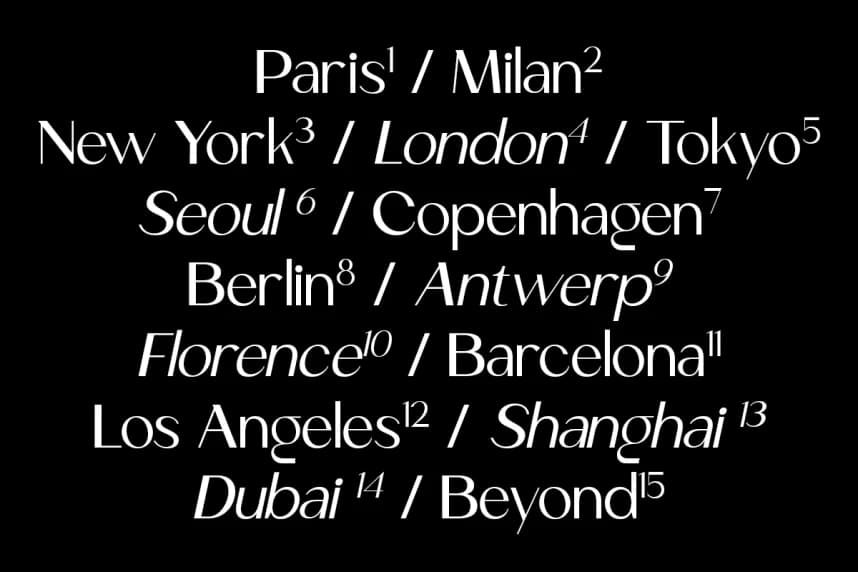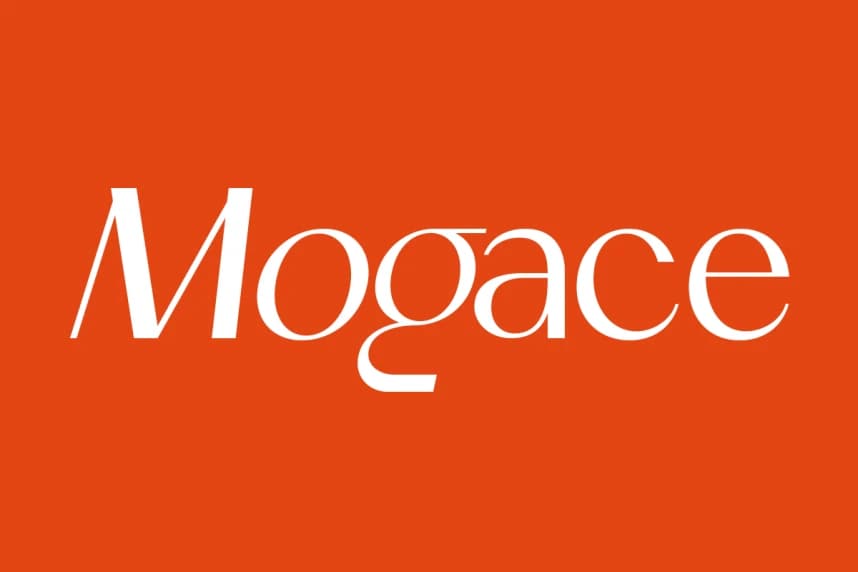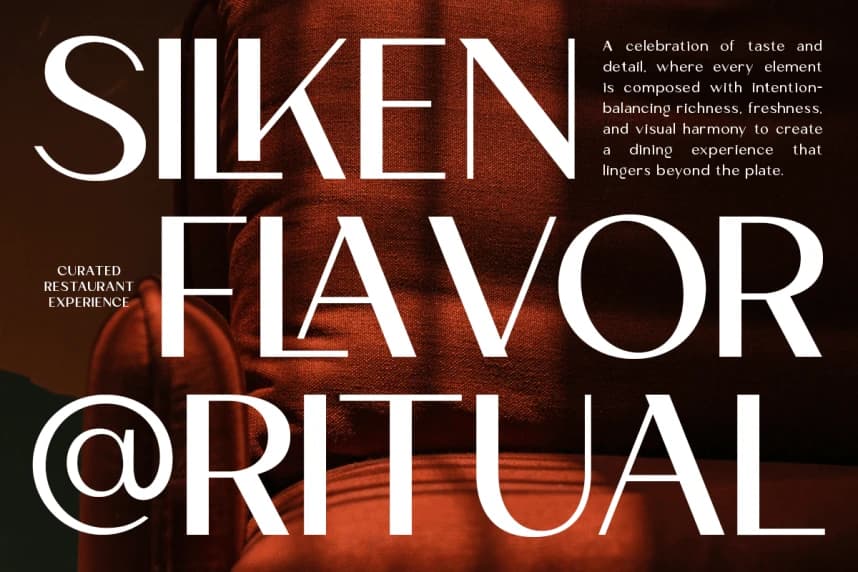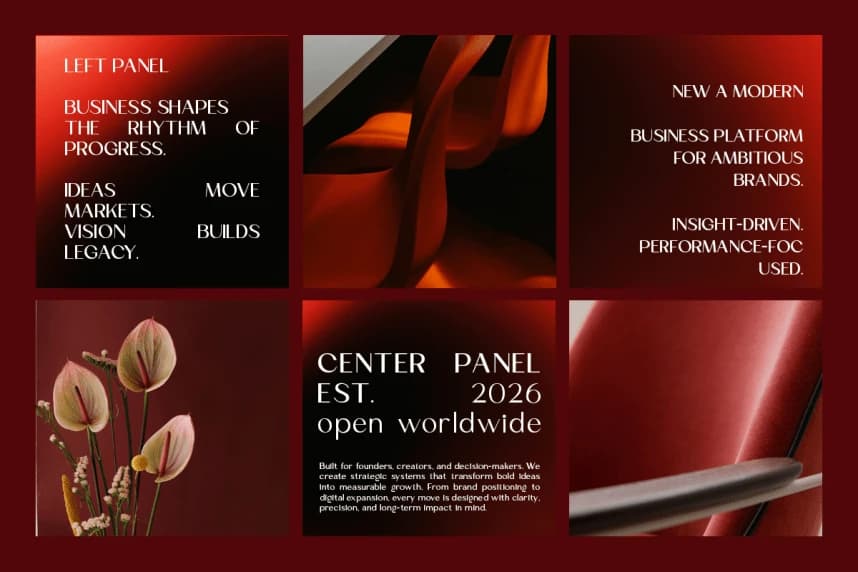
Mogace – Elegant Sans-Serif Font
Mogace – Elegant Sans-Serif Font, zarafet ve görsel sofistike sunmak amacıyla tasarlanmış modern bir editoryal serif tipografisidir. Yüksek kontrastlı hatları, zarif eğrileri ve dikkatle dengelenmiş oranlarıyla.
Mogace – Elegant Sans-Serif Font, zarafeti ve görsel sofistikeliği sunmak için tasarlanmış modern bir editoryal serif yazı tipidir. Yüksek kontrastlı hatlarıyla, zarif eğrileriyle ve dikkatlice dengelenmiş oranlarıyla